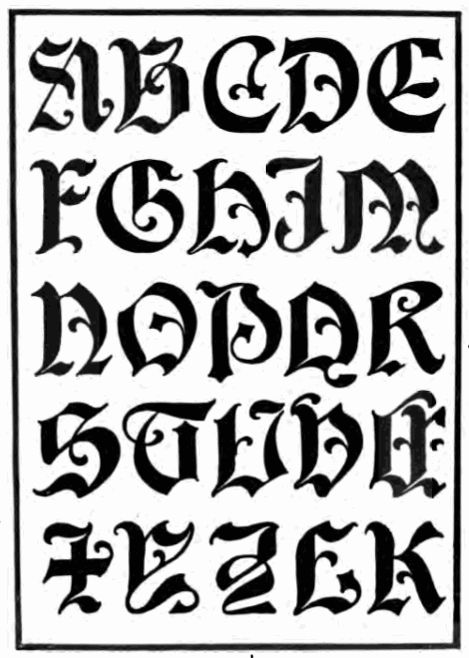
Средневековая типографика: шрифты, которые можно использовать в ваших проектах
Средневековый шрифт, также известный как готический шрифт, является одним из самых элегантных и древних, которые вы только можете найти. Его использование вызывает воспоминания о средневековье, временах рыцарей, замках и битвах между свирепыми воинами.
И хотя сегодня мы давно оставили это время позади, как дизайнер вы можете в какой-то момент столкнуться с проектом, который нуждается в этом типе типографики. Поэтому не повредит, что у вас есть несколько средневековых источников, чтобы вы могли представить различные предложения вашему клиенту, не так ли? Мы говорим о
Средневековая типографика: каково ее происхождение
Средневековый шрифт или готический шрифт, Он был создан в VI веке и его целью было писать на готическом языке., на котором говорили готы. Его происхождение находится в так называемом Codex Argenteus или в его переводе «Серебряная книга или Библия». Это было написано на латыни и было написано епископом Ульфилой. Однако на самом деле это был перевод с греческого языка Библии четвертого века на готский язык.
Если вы заметили, оригинальная готика была вполне «понятной», так как в буквах было не так много атрибутики. Есть также некоторые буквы, которые теперь отличаются тем, что вы сказали бы (например, g выглядит как r; или j выглядит как g).
В средние века этот шрифт был восстановлен и использовался как графический вариант, но придал ему более помпезный стиль.
13 средневековых типографских шрифтов, которые вы можете скачать
Поскольку мы хотим, чтобы у вас был выбор, мы сделали подборку из нескольких средневековых буквенных шрифтов, которые могут быть интересны. И разнообразный. Ваш проект может быть логотипом, плакатом или даже обложкой книги, и, как и во многих других вещах, будет средневековый шрифт, который идеально подходит для каждого проекта.
Готический шрифт Pauls Swirly
Мы начнем со средневекового шрифта, который привлечет ваше внимание из-за своих расцветок. И дело в том, что его дизайн полностью готический.
Теперь вы должны иметь в виду, что это действительно заглавные буквы, которые имеют самый богатый дизайн; строчные буквы, они хоть и готические, но более мягкие.
С одной стороны, это нормально, потому что вы можете использовать заглавные буквы, чтобы привлечь внимание, и строчные буквы, чтобы сообщение было понятно или текст, который вы вводите, читался хорошо.
Монастырь черный
Этот тип средневекового фонтана — один из самых известных, заглавные буквы — это те, которые имеют дизайн с большим количеством расцветок в то время как нижний регистр намного проще.
Старый английский
В этом случае со средневековым шрифтом, который делает ставку на тонкие линии, вы найдете тот, который в нижнем регистре отображается курсивом, но в случае заглавных букв они имеют несколько более любопытный вид, поскольку внутри некоторых букв кажется, что появляется своего рода флаг или рисунок, похожий на один.
Вера рушится
Этот средневековый фонтан — один из тех, которые нам нравятся больше всего.
вид, как туман, который он производит. Идеально, например, для шотландских романов или если вы хотите внести в проект оттенок призрачного, готического, старого и загадочного.
Черная семья
Говорить о Черной семье будет долго. И дело в том, что весь этот средневековый шрифт имеет разные варианты, которые могут помочь вам найти тот, который вам больше нравится. В у вас полностью черный цвет, с некоторой штриховкой, с эффектом рельефа (имитация 3D) и т. д.
Древний
С толстыми мазками Ancient выглядит довольно простым для понимания шрифтом. Да, его макет влияет как на верхний, так и на нижний регистр; и в некоторых случаях кажется, что последние состоят из копий или острия (например, буквы ен).
Средневековый шрифт: Angel Wish
Источник: FFonts
Это одна из средневековые буквенные шрифты только для личного пользования, Это означает, что вы не можете использовать их в коммерческих целях, но знать об этом не помешает.
Он немного толще, чем тот, который мы рекомендовали от Olde English, но по схеме, очень похожей на этот.
Его дизайн направлен на удлинение букв для достижения эффекта чересстрочной развертки между словами.
Руритания
В данном случае у вас средневековый шрифт, который как прописные, так и строчные буквы очень украшены. Это затрудняет чтение во многих случаях, особенно в зависимости от того, какое слово вы вводите. Мы рекомендуем вам не использовать его в слишком большом тексте.
В остальном, несомненно, очень красиво.
Кардинальный
Еще один средневековый шрифт стиля очень элегантно, аккуратно и, что самое главное, разборчиво, это Кардинал. Для него характерна обычно тонкая линия с минимальными деталями (в основном, удлинение некоторых частей определенных букв (прописных и строчных).
Средневековый шрифт: Текст Медичи
Источник: FFonts
Если вы ищете букву, орнамент которой находится в нижней части буквы, этот шрифт может быть идеальным.
Если вы обратите внимание, заглавные буквы имеют много выступов, но почти все они расположены в основании буквы, Хотя строчные буквы несколько четче, они все же затрудняют чтение.
Zenda
Зенда — это средневековый шрифт кларита, как в верхнем, так и в нижнем регистре. Хотя у него есть одна особенность: все строчные буквы имеют диагональные линии, выходящие сверху и снизу. В случае заглавных букв он имеет очень элегантный дизайн между тонкими и толстыми линиями. Попробуйте использовать все слово с большой буквы, чтобы увидеть эффект.
Влад Цепеш II
Можно сказать, что этот шрифт является сценарием, потому что его дизайн очень цветочный, не из-за цветов, а из-за деталей. Это затрудняет чтение, и мы рекомендуем только для отдельных букв, возможно, вы хотите выделить часть, потому что, если вы ее поставите, будут слова, которые ничего не понимают, потому что линии размывают друг друга.
Средневековый шрифт: Frax Handwritten
Ищете средневековый шрифт, похожий на рукописный? Что ж, у вас есть это, Frax Handwritten, от очень простая линия, которая выглядит так, как будто она действительно сделана вручную.
Конечно, прописные и строчные буквы очень просты, что делает их читаемыми (с некоторыми у вас могут возникнуть трудности, особенно с буквами …
Готические — Средневековые шрифты — Fontzzz.com
Страницы: >> 1 2 3 4 5 6 7 8 9 10 КонецШрифт Offenbach Chancery
Автор: The Scriptorium Добавлен: 2012-07-15 Просмотров: 3227 Загрузок: 165
Шрифт Oh My Goth
Автор: Kevin Richey Добавлен: 2012-06-23 Просмотров: 3053 Загрузок: 116
Шрифт Olde Crilt
Автор: RaseOne Full Time Artists Добавлен: 2021-10-30 Просмотров: 511 Загрузок: 7
Шрифт Olde English
Автор: Dieter Steffmann Добавлен: 2012-12-04 Просмотров: 2958 Загрузок: 174
Шрифт Oldprint
Автор: Luca Ricossa Добавлен: 2013-12-14 Просмотров: 2678 Загрузок: 127
Шрифт Old Deutschland
Автор: Добавлен: 2019-07-02 Просмотров: 1699 Загрузок: 98
Шрифт Old Englished Boots
Автор: Добавлен: 2021-01-17 Просмотров: 902 Загрузок: 24
Шрифт Old English Hearts
Автор: Lars Manenschijn Добавлен: 2013-08-17 Просмотров: 3302 Загрузок: 124
Шрифт Old London
Автор: Dieter Steffmann Добавлен: 2013-02-26 Просмотров: 4383 Загрузок: 458
Шрифт Pamela
Автор: Dieter Steffmann Добавлен: 2012-06-16 Просмотров: 3869 Загрузок: 166
Шрифт Pauls Swirly Gothic
Автор: Paul Добавлен: 2012-11-15 Просмотров: 3970 Загрузок: 200
Шрифт Pennybridge 1563
Автор: M?ns Greb?ck Добавлен: 2013-05-24 Просмотров: 2961 Загрузок: 132
Шрифт PentaGram’s Callygraphy
Автор: Добавлен: 2022-08-13 Просмотров: 145 Загрузок: 5
Шрифт Perry Gothic
Автор: DeNada Industries Добавлен: 2012-12-20 Просмотров: 3120 Загрузок: 188
Шрифт Peter Schlemihl
Автор: Dieter Steffmann Добавлен: 2012-09-04 Просмотров: 3087 Загрузок: 152
Шрифт Phalyn
Автор: Razor Graphix Добавлен: 2013-10-07 Просмотров: 2928 Загрузок: 135
Шрифт Phantasinian
Автор: Intellecta Design Добавлен: 2019-08-22 Просмотров: 1482 Загрузок: 96
Шрифт Pillbox Opaque
Автор: Vic Fieger Добавлен: 2012-04-16 Просмотров: 3167 Загрузок: 121
Шрифт Plakat Fraktur
Автор: Dieter Steffmann Добавлен: 2012-07-09 Просмотров: 3197 Загрузок: 180
Шрифт Poppl Fraktur CAT
Автор: Peter Wiegel Добавлен: 2020-07-23 Просмотров: 1194 Загрузок: 39
Страницы: >> 1 2 3 4 5 6 7 8 9 10 Конец30 лучших средневековых шрифтов
Vandelay Design может получать компенсацию от компаний, продуктов и услуг, представленных на нашем сайте.
Для получения более подробной информации, пожалуйста, обратитесь к нашей странице раскрытия информации.
Лучшие средневековые шрифты вызывают ощущение мистики, старомодности и авантюризма.
Если вашему дизайну нужен классический вид с немного фантастическим оттенком, обратите внимание на эти 30 средневековых шрифтов, которые мы нашли для дизайнеров во всем мире. Мы просмотрели тысячи шрифтов, чтобы найти этот вариант.
Драматические шрифты предлагают множество сильных вариантов шрифтов для целого ряда проектов. Вопрос только в том, что вы собираетесь делать со своим средневековым вдохновением.
НЕОГРАНИЧЕННАЯ ЗАГРУЗКА: более 50 миллионов шрифтов и элементов дизайна
Лучшие средневековые шрифты
Когда дело доходит до типографского дизайна, шрифты из этого списка заставят вас задуматься о возможностях. Независимо от того, находятся ли ваши проекты на средневековую тематику в производстве или просто концептуально, этот набор шрифтов хорошо иметь под рукой, когда они вам понадобятся.
Если вы любите шрифты, вам определенно стоит попробовать Envato Elements. Подписавшись на Elements, вы получите 90 013 неограниченных загрузок 25 000 шрифтов , а также миллионов других ресурсов , таких как темы WordPress, стоковые фотографии, графика, звуковые эффекты и многое другое. Это лучшая ценность, которую вы можете найти в индустрии дизайна.
The Ancient — Medieval Sans Typeface
The Ancient — это эпический шрифт, который вызывает ассоциации с высоким фэнтези и средневековыми приключениями. Наиболее впечатляюще то, что он имеет богато украшенный вид без засечек. Увлекательное письмо украшено уникальными функциями, и его стоит добавить в ваш набор инструментов для дизайна.
Belmont
Belmont — семейство средневековых шрифтов с громким названием. Он вызывает ассоциации с рыцарями и героями и отлично выглядит при этом. Belmont использует прописные многоязычные буквы, альтернативы, цифры и знаки препинания. Учтите это при разработке дизайна вашей следующей фэнтезийной приключенческой игры.
Astaroth — Средневековый дисплейный шрифт
Astaroth — шрифт средневекового дизайна с массивной современной готической эстетикой. Высокие буквы имеют особое присутствие, а характер шрифта, состоящего только из заглавных букв, делает его отличным выбором для заголовков. Рассмотрите его для своих игровых дополнений или постеров на средневековую тематику.
Cambridge
Cambridge — внушительный готический шрифт, излучающий класс. Этот рукописный шрифт смелый и имеет темный средневековый вид, который пойдет на пользу истории о вампирах или любому дизайн-проекту, посвященному охоте на монстров.
Рассмотрите этот вариант для логотипов фильмов, постеров или компонентов игрового дизайна. Он отлично подходит для любого количества пар шрифтов blackletter.
Black Cameo
Готические шрифты и шрифты в средневековом стиле, как правило, объединяют из-за их исторической близости, но они часто вполне взаимозаменяемы во многих дизайнерских проектах.
Из тысяч шрифтов в Интернете со средневековой тематикой Black Cameo уникален тем, что он абсолютно кричит «используй меня» для логотипов металлических групп. Включенные стилистические наборы отлично подходят для любого количества личных проектов, но идеально подходят для логотипа группы.
Iron Steel
IronSteel — это уникальный средневековый дизайн шрифта, который кажется более поздним по сравнению с большинством других причудливых шрифтов в этом списке. Блочный, ксилографический стиль этого шрифта создает элегантное сочетание шрифта с более мелкими шрифтами. Это хедлайнер, который немного современнее.
Serkan
Serkan занимает важное место среди средневековых каллиграфических шрифтов в этом списке, учитывая его кельтский стиль. Этот высококачественный шрифт имеет прекрасные каллиграфические буквы с кривыми и наскоками. Как элегантный дисплейный шрифт, он лучше всего подходит для заголовков и брендинга.
Cattedrale
Cattedrale — это готический шрифт blackletter для дизайнов, которые нуждаются в эффекте.
Из смелых шрифтов в списке этот кажется наиболее близким к хоррору, но он все еще прочно относится к лагерю шрифтов в средневековом стиле. Орнаменты — отличное дополнение, превращающее этот шрифт в один из самых декоративных в списке.
Medieval Times
Medieval Times — одна из самых современных версий средневековых букв в этом списке. Прекрасные, элегантные мазки мало чем отличаются от мазков придворного писца. Этот красивый, изогнутый шрифт подходит для любого проекта, которому нужна мягкость с оттенком средневековья.
Lodbrok
Lodbrok — это акцидентный шрифт в кельтском стиле с красивыми и элегантными округлыми формами букв. Этот каллиграфический шрифт вдохновлен унциальным и готическим курсивом. Несмотря на сложные формы букв, Lodbrok вполне удобочитаем и подходит для любого количества проектов.
Aceking
Aceking — это готический шрифт blackletter, солидный на вид и довольно внушительный. Этот экранный шрифт хорошо подходит для более темных и резких дизайнов и проектов в средневековом стиле.
Работаете над материалом для следующей большой фэнтезийной настольной игры? Взгляните на Aceking, потому что он обязательно вас вдохновит. Используйте его с максимально возможным размером шрифта для максимального эффекта.
Osgard Pro
Osgard Pro — тщательно продуманный шрифт, который отлично подходит для титров и заголовков. Дизайнер описывает его как «жидкий» и «извилистый», а шрифт во многом заимствован из романского стиля и готического шрифта. Этот шрифт напоминает средневековый шрифт, но при этом достаточно современный и является признаком люксового бренда, как и любой другой.
The Quironax — средневековый дисплейный шрифт
Мы не можем сказать вам, что такое Quironax, но мы можем подтвердить, что Quironax — отличный средневековый дисплейный шрифт. Смелый и сложный, он был разработан специально для крупных шрифтов и рисунков. С 720 глифами в обычной и наклонной форме этот шрифт вполне удобочитаем, а специальные альтернативы добавляют массу стиля.
Это солидный формальный рукописный шрифт.
НЕОГРАНИЧЕННАЯ ЗАГРУЗКА: более 50 миллионов дополнений и дизайнерских ресурсов
Первое правление (шесть средневековых шрифтов)
Первое из нескольких «правлений» начинается с Первого правления Мана Гербака. Это одно из пяти различных семейств имеет кельтское влияние с закрученными украшениями в верхнем регистре. Шрифт, как и другие в этой серии, имеет версию с рамками, которая позволяет First Reign оказывать влияние на любой дизайн.
Second Reign (5 средневековых шрифтов)
Second Reign, часть серии Манса Гербака, имеет округлые, сложные буквы и большое разнообразие. Этот шрифт имеет магическое качество и подходит волшебникам и рыцарям соответственно.
Особенно интересны закругленные формы букв «О» и «М». Как и в случае с другими шрифтами из серии Gerback «Reign», существует версия шрифта с рамками для дополнительного украшения.
Third Reign (5 средневековых шрифтов)
Третья серия — дизайн Манса Гребака.
Third Reign имеет больше влияния викингов на дизайн, с большим количеством геральдики и границ для создания впечатляющих средневековых дизайнов. Как и другие члены серии типографики, этот шрифт поставляется с бордюрными и обычными стилями, подходящими для разных проектов.
Fourth Reign
Продолжая серию шрифтов Mans Greback, Fourth Reign — еще один средневековый шрифт с геральдикой. Алмазы, рамки и орнаменты делают этот шрифт отличным выбором для дизайнов, которые должны драматично передать королевский образ.
Fifth Reign
Fifth Reign — смелый средневековый шрифт, разработанный Мансом Гребаком. Этот шрифт больше предназначен для декоративного использования из-за впечатляющего, хотя и немного драматичного орнамента в дизайне. Шрифт имеет эпический вид, и его лучше всего использовать для привлечения внимания в сочетании с некоторыми более простыми шрифтами для передачи большего количества информации.
Nottingshire
Nottingshire — это современный шрифт с засечками, на который не оказывает особого влияния существующий шрифт.
Дизайн больше заимствован из общего фэнтези и средневекового дизайна, чем-то, что может работать как возврат, но может использоваться для современных интерфейсов. Один из самых очаровательных каллиграфических шрифтов, которые вы увидите в списке.
England
England — это шрифт, созданный под влиянием прокрутки средневековья. Из вариантов типографики в средневековом стиле в списке это один из самых уникальных с блочными, четкими формами букв с особенно динамичными завитушками. England — это шрифт, который стоит скачать.
She Dance
She Dance — отличный выбор для дизайнерских проектов, требующих кельтского стиля. В равной степени современный и классический по эстетике, этот шрифт может придать уникальный вид любому дизайну. Он содержит прописные, строчные и обычные символы, включая лигатуры и альтернативы.
Ring of Kerry
Если вы ищете фон, напоминающий Ирландию и кельтский стиль, то Ring of Kerry не просто подходит… он имеет подходящее название! Этот шрифт представляет собой декоративный стиль отображения, напоминающий Ирландию, и содержит символы в виде кругов.
Есть также множество альтернатив и некоторые кельтские узлы.
Vinque
Vinque — это шрифт декоративно-прикладного искусства с традиционной красивой природой. Формы букв напоминают средневековые стили, потому что они взяты из возрождений 19-го века. Шрифт кажется чем-то старым, но без чрезмерного выбора декоративного дизайна.
Bricius
Bricus — впечатляющий кельтский шрифт, идеально подходящий для использования на дисплеях. Этот шрифт использует элементы современного дизайна, но прислушивается к древней эстетике со специальными альтернативами, лигатурами и каллиграфическими штрихами. Многоязычная поддержка также предоставляет фантастические возможности, когда вы стремитесь к чему-то более «фантастическому» в утонченном дизайне.
Луносвет — средневековый шрифт
Луносвет — прекрасный мультяшный средневековый шрифт. Надпись напоминает нечто более руническое, чем то, что традиционно считается средневековым, и имеет расцветку шрифта, используемого в брендинге видеоигр.
Зубчатые формы букв представляют напористое и древнее отношение и построены вокруг треугольных форм. Попробуйте этот шрифт дисплея.
Жанна д’Арк
Жанна д’Арк — фонтанный шрифт в средневековом стиле. Он отличается красивыми и элегантными линиями, которые дополняют традиционный стиль письма. Даже тогда он по-прежнему яркий, с красивыми завитушками на засечках и почти каждой заглавной буквой.
Бесплатные средневековые шрифты
Эти коммерческие бесплатные шрифты вдохновлены средневековьем и являются отличным выбором для начинающих дизайнеров и проектов. Как всегда, даже с этими шрифтами в средневековом стиле вы должны самостоятельно проверять лицензии.
Goudy Medieval
Goudy Medieval — прекрасный шрифт, который выглядит как ранняя блочная печать из ранних портфолио. Типографский дизайн Дитера Штеффманна неподвластен времени, но не слишком привязан к определенному стилю, и бесплатная лицензия приветствуется. Goudy Medieval стоит скачать, чтобы иметь под рукой.
Kingthings Exeter
Kingthings Exeter — это шрифт с каллиграфическими завитушками, вызывающими средневековье. Kingthings Exeter, несомненно, является надежным выбором для каллиграфии и довольно удобочитаемым для загрузки — шрифт исключительно хорошо сочетается со своим родным братом Kingthings Foundation. Тем не менее, обязательно просмотрите лицензионную информацию о том, как дизайнеры могут использовать ее в коммерческих проектах.
Kingthings Foundation
Kingthings Foundation — это каллиграфический шрифт с царственным видом благодаря завитушкам на засечках. Шрифт напоминает «Ye Olde Days» и является отличным средневековым шрифтом для личного проекта. Однако проверьте лицензию для получения информации о коммерческих проектах.
Ringbearer
Ringbearer — это бесплатный шрифт для личного использования. Это все, что мы можем порекомендовать, поскольку это довольно близкая копия культовой надписи логотипа экранизации Питера Джексона классической трилогии «Властелин колец».
Шрифт очарователен и тщательно воспроизведен, но его лучше всего использовать для практики или личных проектов.
Mael
Mael — это бесплатный шрифт, лицензированный для личного и коммерческого использования, так что вы можете использовать его в любых мифических или фантастических проектах. Заостренные элементы шрифта и маленькие плотные петли создают несколько необычный, но мистический выбор шрифта. Придайте вашим личным проектам нотку благородства вместе с Mael.
Начните использовать эти средневековые шрифты сегодня
Средневековые шрифты из этого списка пригодятся для любого количества будущих проектов в вашем списке. Независимо от того, ищете ли вы рукописные буквы или логотипы в стиле фантастической книги, эта сборка полна дизайнерского вдохновения. Подходит для работы в жанре фэнтези и декоративной графики, ваше единственное ограничение — ваше воображение и место на холсте.
20 бесплатных средневековых шрифтов для уникальных дизайнов Line25
04 июля 2017 г.
— (обновлено 10 июля 2022 г.)Line25 поддерживается пользователями нашего веб-сайта. Бесплатно для вас партнерская комиссия может быть получена при совершении покупки по различным ссылкам на нашем сайте. Узнать больше
Этот обзор бесплатных шрифтов немного более специфичен и создан для нишевых дизайнов и проектов. Мы решили найти лучшие бесплатные средневековые шрифты с уникальным дизайном! Откройте для себя эти выдающиеся средневековые шрифты и используйте их в своих проектах, вдохновленных Средневековьем. Эти бесплатные средневековые шрифты можно использовать в любом дизайне, где вы чувствуете необходимость добавить немного фантазии, а также немного шарма.
Обновлено 6 июля 2022 г.
Дизайн каждого шрифта уникален и не оставит равнодушными ваших пользователей! Они, несомненно, добавят характера любому проекту, в который вы их интегрируете, и упростят демонстрацию вашего персонализированного контента.
Есть множество проектов, в которых вы можете использовать эти бесплатные средневековые шрифты.
Некоторые из них могут включать книги, плакаты, различную декоративную графику, игры и многое другое. Эти шрифты включают в себя различные украшения и сложные конструкции.
Обязательно проверяйте лицензию каждого файла. Некоторые из них можно использовать только в личных проектах, а другие доступны как для коммерческих, так и для личных работ.
Хотите больше похожих бесплатных шрифтов? Проверьте эти бесплатных готических шрифтов и драматические шрифты .
Этот красивый средневековый шрифт был создан Альдусом. Он доступен для бесплатного скачивания и может использоваться как в личных, так и в коммерческих проектах.
Black Baron — средневековый шрифт. Он содержит все прописные и строчные английские буквы от A до Z, цифры от 0 до 9, знаки препинания, альтернативные глифы и лигатуры. Этот декоративный шрифт, вдохновленный готическим и староанглийским шрифтом, лучше всего подходит для журналов, логотипов, плакатов, фестивалей и товаров.
Контакт
Вот удивительный шрифт в готическом стиле, который вы можете скачать бесплатно и использовать в некоммерческих проектах. Pin
Osgard Pro — элегантный шрифт с засечками. Он включает 1000 росчерков, лигатур соединений, стилистических альтернатив и функций OpenType. Osgard хорошо подходит для средневековых и фантастических приложений, логотипов, редакционных статей и моды, сочетая изогнутые элементы романской типографики и готического стиля Blackletter. Pin
Это уникальный шрифт с креативным дизайном. Лицензия этого файла неизвестна, поэтому обязательно свяжитесь с автором, если хотите использовать его в коммерческих проектах.
PinHeraldry — это дингбат-шрифт. Он содержит 124 символа, которые отдают дань уважения гербам королевских европейских семей. Используйте эти символы, чтобы воссоздавать щиты и украшать свои проекты. Pin
Это облегченный шрифт, который вы можете загрузить и использовать бесплатно только в личных проектах. Если вы хотите использовать его в коммерческих проектах, свяжитесь с автором.
Pin
Dutch Brigade — современный шрифт Blackletter. Он содержит прописные и строчные английские буквы A-Z, цифры 0-9., символы, пунктуация, чередование стилей и лигатуры, а также поддерживает многоязычные акценты. Голландская бригада орнаментальна со стилистическими складками по всему шрифту. Его стильный дизайн идеально подходит для парикмахерских, вывесок, прайс-листов, оконной графики и одежды.
PinЭто выдающийся шрифт в готическом стиле с привлекательным дизайном. Вы можете скачать его бесплатно и интегрировать в свои текущие или будущие проекты.
Pin Gothicha — искусно созданный элегантный средневековый шрифт с засечками. Он содержит все заглавные английские буквы A-Z, цифры 0-9., специальные символы, знаки препинания, чередование стилей, лигатуры, параметр контурного шрифта и поддержка многоязычных акцентов. Формы Gothicha создают потрясающие визуальные эффекты и подходят для логотипов, свадебного дизайна, упаковки, этикеток, фотографий, водяных знаков и канцелярских товаров.
Pin
Посмотрите на этот красивый средневековый шрифт, который вы можете использовать в своих будущих проектах. Этот шрифт имеет потрясающий дизайн и может использоваться как в личных, так и в коммерческих целях.
PinЗдесь у вас есть уникальный средневековый дизайн шрифта, который вы можете использовать в личных целях. Пожалуйста, свяжитесь с дизайнером, если вы хотите использовать его в коммерческих проектах. Пин
Этот шрифт в готическом стиле имеет удивительный дизайн, который обязательно привлечет внимание вашего пользователя. Пожалуйста, проверьте файл лицензии, чтобы убедиться, что вы используете его в соответствии с требованиями дизайнера.
PinУдивительный средневековый шрифт с уникальным дизайном. Вы можете использовать этот шрифт как в коммерческих, так и в некоммерческих проектах. PIN
Вот вам замечательный средневековый шрифт с рукописным дизайном. Этот каллиграфический шрифт может быть интегрирован в личные проекты, а также в коммерческие, с согласия автора.
Пин
Еще один замечательный шрифт, созданный под влиянием средневековья. Загрузите этот шрифт, используйте его в своих проектах, и вы обязательно произведете впечатление. Pin
Этот уникальный шрифт имеет тщательно продуманный дизайн и доступен в двух вариантах. Вы можете использовать его как в личных, так и в коммерческих проектах.
PinУдивительный средневековый шрифт, который можно сразу использовать в некоммерческих проектах. Дизайн персонажа несколько прост, но с небольшой изюминкой, которая делает его особенным. Пин
Это выдающийся шрифт в готическом стиле, который обязательно будет замечен в ваших проектах. Вы можете скачать этот шрифт бесплатно и использовать его как в личном, так и в коммерческом дизайне в соответствии с вашими требованиями. PIN-код
Этот легкий шрифт имеет уникальные символы, которые выделяют его среди остальных. Вы можете скачать этот шрифт бесплатно и использовать его в любых проектах. Pin
Этот сильный шрифт имеет прекрасный дизайн, который будет отлично отображаться во многих проектах.
Вы можете использовать его в личных или коммерческих целях.
Еще один средневековый шрифт с выдающимся дизайном. Добавьте индивидуальности своим проектам, интегрировав этот шрифт. PIN-код
Это исключительный шрифт с потрясающим дизайном, который обязательно привлечет внимание вашего пользователя. Этот шрифт доступен бесплатно только для личных проектов. Pin
Это потрясающий шрифт со средневековым вдохновением. Этот шрифт будет отлично отображаться в личных проектах. Более того, он доступен бесплатно.
Этот шрифт включает в себя очень детализированные символы, которые обязательно будут замечены, независимо от того, в каком проекте вы их используете. Шрифт доступен для бесплатной загрузки и может использоваться в личных проектах.
27 Мощные средневековые шрифты времен лордов, дам и епископов
Последнее обновление: 14 июня 2022 г.
Одним из периодов в истории человечества, который очаровал многих людей, является Средневековье. Кто может устоять перед историями о рыцарях, дамах, королях и королевах?
В какой-то степени, возможно, вы тоже мечтали смотреть вниз с башни, когда трубадур пел вам серенаду.
Или, может быть, вы задавались вопросом, на что похожа жизнь рыцаря: с боями на мечах, битвами и рыцарством.
Средневековье, Средневековье и Темные века
Хронология средневековья охватывает период с 500 по 1500 год нашей эры, что составляет примерно 1000 лет. Большинству людей нравится использовать три термина — средние века, средневековье и темные века — взаимозаменяемо. Но эксперты скажут вам, что есть небольшие различия.
средних веков относятся к временной шкале от падения Рима до начала Ренессанса. Ученые также предпочитают называть эту эпоху 9-й0013 средневековый период . Многие знакомы с последним термином, потому что он напоминает о замках, монастырях, соборах, крестьянах и крестовых походах.
темные века , с другой стороны, это то, что историки любят называть периодом, когда после падения Рима мало что было известно. Таким образом, все осталось в «темноте».
Важные события Средневековья
Возможно, одним из самых печально известных событий Средневековья была Черная смерть.
Тогда 9Таинственная чума 0013 , теперь известная как бубонная чума, унесла жизни более 20 миллионов человек, что составляет примерно 30 процентов населения Европы. Из-за тесноты городов, плохой гигиены и недостатка знаний в медицине болезнь легко передавалась и длилась около трех лет.
Еще одним печально известным событием того времени стал крестовый поход . Начатые в 1095 году папой Урбаном, когда он приказал христианской армии идти в Иерусалим, сражения продолжались до 15 века. Одним из признаков того, что крестовые походы в конце концов подошли к концу, стала осада Акры в 129 г.1. В 1312 году даже знаменитые рыцарей-тамплиеров были распущены.
Многие специалисты связывают средневековье с двумя вещами: варварством и религией. Преданность церкви породила романские соборы и монастыри. До изобретения и массового использования печатного станка существовали рукописи ручной работы, написанные золотым и серебряным шрифтом с замысловатыми украшениями и священными иллюстрациями.
Средневековье было не только временем варварства, чумы и темной архитектуры. Мы надеемся, что эти потрясающие средневековые шрифты помогут вам продемонстрировать, что было хорошего и прекрасного в ту непонятую эпоху.
1. Hikma — шрифт в арабском стилеHikma — уникальный шрифт в арабском стиле с 35 красивыми лигатурами. Вдохновленный великолепной арабской каллиграфией, этот шрифт подходит для любого исламского или ближневосточного контента. Hikma идеально подходит для брендинга, фотографии, дизайна продуктов, канцелярских принадлежностей, свадебного дизайна, приглашений, водяных знаков, рекламы, этикеток, упаковки продуктов, специальных мероприятий и многого другого.
Скачать Hikma Typeface
2. Pollyester Blackletter Этот острый декоративный шрифт с засечками, разработанный Maulana Creative , выполнен вручную и выглядит как замысловатая надпись прошлых дней.
Пакет поставляется с лигатурами, стилистикой и включает многоязычную поддержку для вашего удобства.
Download Pollyester Blackletter
3. GreatwoodsХардкорная и написанная от руки, эта готическая жемчужина из Typia Nesia Std может быть таким темным или стильным, как вы хотите — все зависит от вашего воображения. Используйте его на футболках, обложках альбомов, логотипах, плакатах, редакционных статьях и блогах, главное, чтобы вы получали от этого удовольствие!
Download Greatwoods
4. Distorsi BlacklettersВдохновленный метал-группами, Holismjd создал эту единственную в своем роде сцену, которая даже сама по себе sans-stealers. Продолжайте качаться, применяя его к своим фотографиям, музыкальным обложкам, одежде и многому другому.
Скачать Distorsi Blackletters
5. Poison Freak Декоративный шрифт без засечек от Alit_Design , вдохновленный черным шрифтом, напоминающим готический стиль старого мира.
Этот продукт, настроенный для современного поколения, поставляется с набором бонусных векторов, который вы можете настроить в соответствии со своими потребностями.
Download Poison Freak
6. Solaire RoughMehmetRehaTugcu с гордостью представляет этот фэнтезийный шрифт с руническим оттенком, который будет потрясающе смотреться на ваших плакатах, дизайне игр и обложках книг. Используйте заглавные буквы для переключения между вариантами (доступно только для выбранных букв), чтобы придать своим работам больше характера.
Скачать Solaire Rough
7. ЛивингстонНужно что-то яркое для старинных винных этикеток или логотипов старой школы? Тогда загрузите этот декоративный шрифт Blackletter к StringLabs .
Download Livingstone
8. Wilson Wells Этот серьезный готический шрифт blackletter не нуждается в представлении.
Он поставляется со стилистическими альтернативами, лигатурами, многоязычной поддержкой и даже работает в Microsoft Word.
Download Wilson Wells
9. Old CharlotteСмелый, сильный и вневременной, этот готический шрифт из Naulicrea — это все, что вам нужно, чтобы создать ту потустороннюю мрачную атмосферу, которую вы видели в фильмах о вампирах и средневековье, за исключением того, что этот фильм читабелен, совершенно великолепен и имеет современные влияния.
Скачать Old Charlotte
10. AcekingКак говорится, не идут в бой с пустыми руками. В битве за лучшую типографику вам нужно что-то прочное, надежное и способное выстоять — как этот красивый винтажный дисплейный шрифт.
Скачать Aceking
11. Restora Neue Bold Этот шрифт из набора Nasir-Udin отличается более аккуратной формой и повышенной контрастностью.
Достаточно универсальный, чтобы его можно было использовать на обложках книг, упаковках продуктов и визитных карточках, он также достаточно уникален, чтобы его можно было применять для брендинга и редакционных статей.
Скачать Restora Neue Bold
12. MythshireСозданный Twinbrush , рукописный текст отличается индивидуальностью и наполнен полным набором альтернативных символов (прописных и строчных), а также более 40 лигатур для игры. Элегантный, органичный и немного средневековый, этот шрифт станет вашим идеальным шрифтом для всего, что связано со Средневековьем.
Download Mythshire
13. RozexБудь то татуировка или шаблон для настенной росписи, этот декоративный шрифт с засечками обладает характером и отношением, которое обладает полным эффектом.
Загрузить Rozex
14. Brightfate Этот полужирный шрифт с засечками представляет собой сочетание средневекового стиля письма с темами городской уличной одежды.
Разработанный Reza Rasenda и Riska Candra Dewi , продукт включает альтернативы, лигатуры, стилистику и многоязычную поддержку.
Скачать Brightfate
15. Bullgine BlackletterLetterhend представляет этот современный готический блэклеттер, который можно применять как в профессиональных, так и в неформальных проектах. Вы можете получить доступ ко всем вариантам глифов при использовании таких программ, как приложения Adobe и Corel Draw.
Скачать Bullgine Blackletter
16. LordishПримите свою темную сторону в этом уникальном шрифте blackletter от CreativeMediaLab . Он будет потрясающе смотреться на вашей одежде, татуировках, обложках альбомов, плакатах, этикетках и многом другом. Продукт также поставляется с орнаментами и шаблонами логотипов.
Скачать Lordish
17.
Odd Times Gleb_Guralnyk предлагает вам средневековый шрифт blackletter под влиянием старой каллиграфии изломов. Декоративный с рукописными штрихами, его лучше всего использовать на одежде, плакатах, обложках книг и брендинге.
Скачать Odd Times
18. Черный баронПлотно-черный со слегка декорированными крышками и угловатыми формами, Mihis_Design дает вам этот средневековый шрифт с засечками, который более царственный, чем кажется. Благодаря своей современной привлекательности и чередованию тонких и толстых штрихов, он достаточно гибкий, чтобы его можно было применить практически к любому проекту.
Скачать Black Baron
19. Belmont Regular Воплотите эти фантастические темы в жизнь, используя это средневековое семейство шрифтов из MehmetRehaTugcu . Его чистый внешний вид и черты старой школы придают правильный стиль логотипам, обложкам книг и плакатам.
Скачать Belmont Regular
20. The AncientПроизведите впечатление на публику и клиентов, применяя этот средневековый гротеск к своим работам. Мощный, четкий, но сохраняющий удобочитаемость, это идеальный шрифт для открыток, логотипов, визитных карточек, обложек книг, игровых приложений и веб-страниц, которые восходят к временам лордов и рыцарей.
Скачать The Ancient
21. Candelabra — это набор средневековых шрифтов, полный лигатур, цифр и пунктуации. Включает в себя набор из 8 стилей слоя с высоким разрешением, а также 10 бликов для добавления волшебного завершающего штриха!
Скачать Candelabra
22. Arkana Arkana — захватывающий фэнтезийный шрифт. Он включает в себя прописные и строчные буквы, специальные символы, цифры и знаки препинания. Вы можете использовать этот шрифт для различных проектов.
Он идеально подходит для книг, видеоигр, фильмов или любых других публикаций или производства в жанре фэнтези.
Скачать Arkana
23. Шрифт Black Pytter
Black Pytter — это шрифт, вдохновленный шрифтом Blackletter, выполненный в современном стиле, но при этом выглядящий сильным и уникальным. Поддерживается альтернативными вариантами, такими как перекос, лигатура и альтернативные символы, что делает шрифт Black Pytter очень удобным для создания дизайнов с яркими или темными темами. Кроме того, шрифт The Black Pytter также поддерживает многоязычные символы, которые можно использовать на нескольких международных языках.
Шрифт Black Pytter очень подходит для использования в дизайне обложек музыкальных альбомов, тату-логотипов, этикеток для виски, упаковки помад и т. д., которые созданы с использованием темных и сильных концепций.
Загрузите шрифт Black Pytter здесь!
24. Шрифт Maboth
Maboth — великолепный средневековый шрифт, вдохновленный шрифтом Blackletter.
Он создан, чтобы производить впечатление современности, но по-прежнему выглядит сильным, уникальным и по-своему винтажным.
Поддерживается альтернативными параметрами, такими как перекос, лигатура и альтернативные символы, что делает гарнитуру Maboth очень простой для создания дизайнов с яркими или темными темами. Кроме того, шрифт The Maboth Typeface также поддерживает многоязычные символы, которые можно использовать на нескольких международных языках.
25. Hello MyToys Blackletter
Hello MyToys отличается индивидуальностью и содержит полный набор альтернативных символов (прописных и строчных), а также более 20 лигатур для игры. Элегантный, органичный и немного средневековый, этот шрифт станет вашим идеальным шрифтом для всего, что связано со Средневековьем.
26. Шрифт King Castle Celtic
Элегантный шрифт в кельтском стиле. Этот уникальный дисплейный шрифт вдохновлен кельтскими стилями.